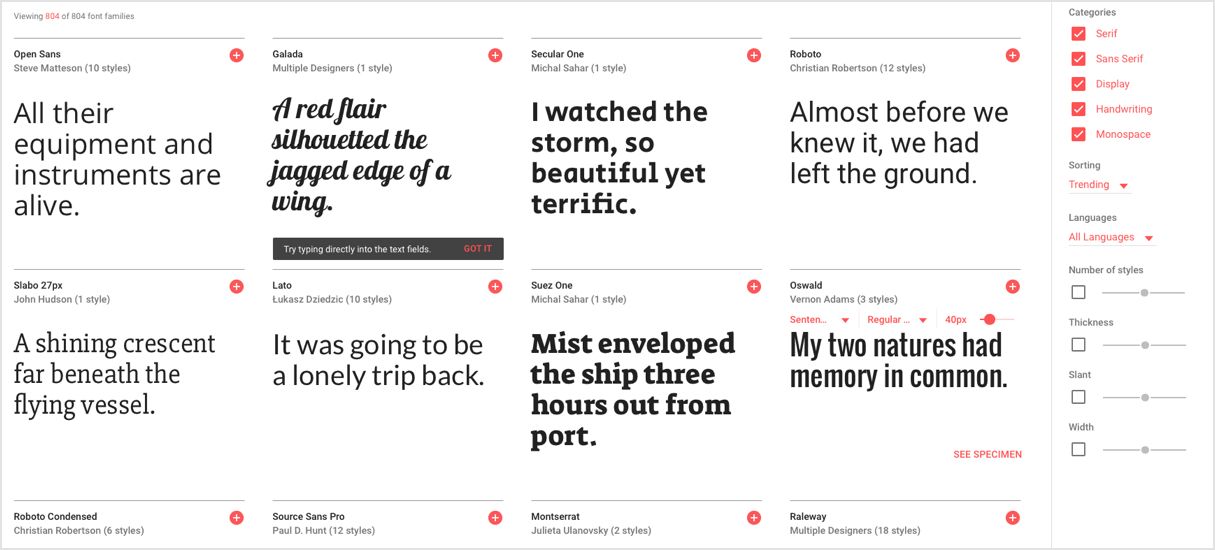
Памятка по веб-шрифтам: Бесплатные шрифты Google Альтернативы Futura и тому подобное
У вас ограниченный бюджет, и вы не можете позволить себе покупку дорогих шрифтов для своего веб-сайта? Ознакомьтесь с бесплатными альтернативами Google, которые мы рассмотрели в этом посте.
Мы знаем, что поиск идеального веб-шрифта для вашего веб-сайта может быть довольно сложным. Особенно, когда у вас ограниченный бюджет и покупка широко используемых шрифтов, таких как Proxima Nova или Futura, не вариант. К счастью, есть достойные бесплатные шрифты, которые на самом деле очень хорошо сочетаются друг с другом.
Шрифты Google — идеальная замена шрифтам Futura и другим коммерческим шрифтам
Шрифты Google — это каталог бесплатных шрифтов, которые каждый может добавить на свой сайт. Он ставит типографику «на передний план». Коллекция была тщательно отобрана дизайнерами, сообществом открытого исходного кода и инженерами. Он доступен для изучения на более чем 135 языках.
Среди шрифтов Google вы можете найти бесплатную альтернативу почти каждому шрифту премиум-класса, например шрифту Futura или ему подобным. Шрифты, доступные в каталоге, также увеличивают скорость веб-страницы. Это достигается благодаря межсайтовому кэшированию. Просто загрузите шрифт один раз, и он будет доступен на любом веб-сайте, использующем шрифты Google.
Чтобы помочь вам сэкономить массу времени, мы составили краткое руководство по популярным премиум-шрифтам и их лучшим заменителям шрифтов Google. Наслаждаться!
14 лучших альтернатив Google Font для популярных шрифтовВот полный список изученных нами веб-шрифтов:
- Helvetica >>> Open Sans
- Helvetica >>> Arimo Sans Helvetica
- Фрутигер >>> Хинд
- Футура >>> Нунито
- Futura>>> Kumbh Sans
- Futura>>> Questrial
- Baskerville >>> Libre Baskerville
- Proxima Nova >>> Montserrat
- Adobe Caslon >>> Lusitana
- Neo Sans 904 >>> Meta Web Pro >>> Source Sans Pro
- FF DIN >>> Roboto
- Poster Bodoni >>> Abril Fatface
Helvetica — это шрифт без засечек с довольно старой историей, восходящей к 1961 году, доступный для 80 языков. Open Sans — это бесплатная альтернатива шрифту от Google, которую вы можете использовать вместо Helvetica.
Он был разработан Стивом Маттесоном и содержит около 900 символов, включая кириллицу и греческий язык.
Другим вариантом, который вы можете рассмотреть в качестве замены Helvetica, является шрифт Google Bebas Neue. Он был разработан Ryoichi Tsunekawa и лучше всего подходит для подписей и заголовков.
Arimo — еще одна альтернатива Helvetica Google FontСозданная Стивом Маттесоном, эта современная альтернатива шрифту Helvetica Google великолепна с точки зрения удобочитаемости на экране и позволяет разработчикам решать проблемы переносимости документов между платформами. Символы в Arimo немного выше, чем в веб-шрифте Helvetica. Этот шрифт без засечек имеет 4 насыщенности и включает курсив.